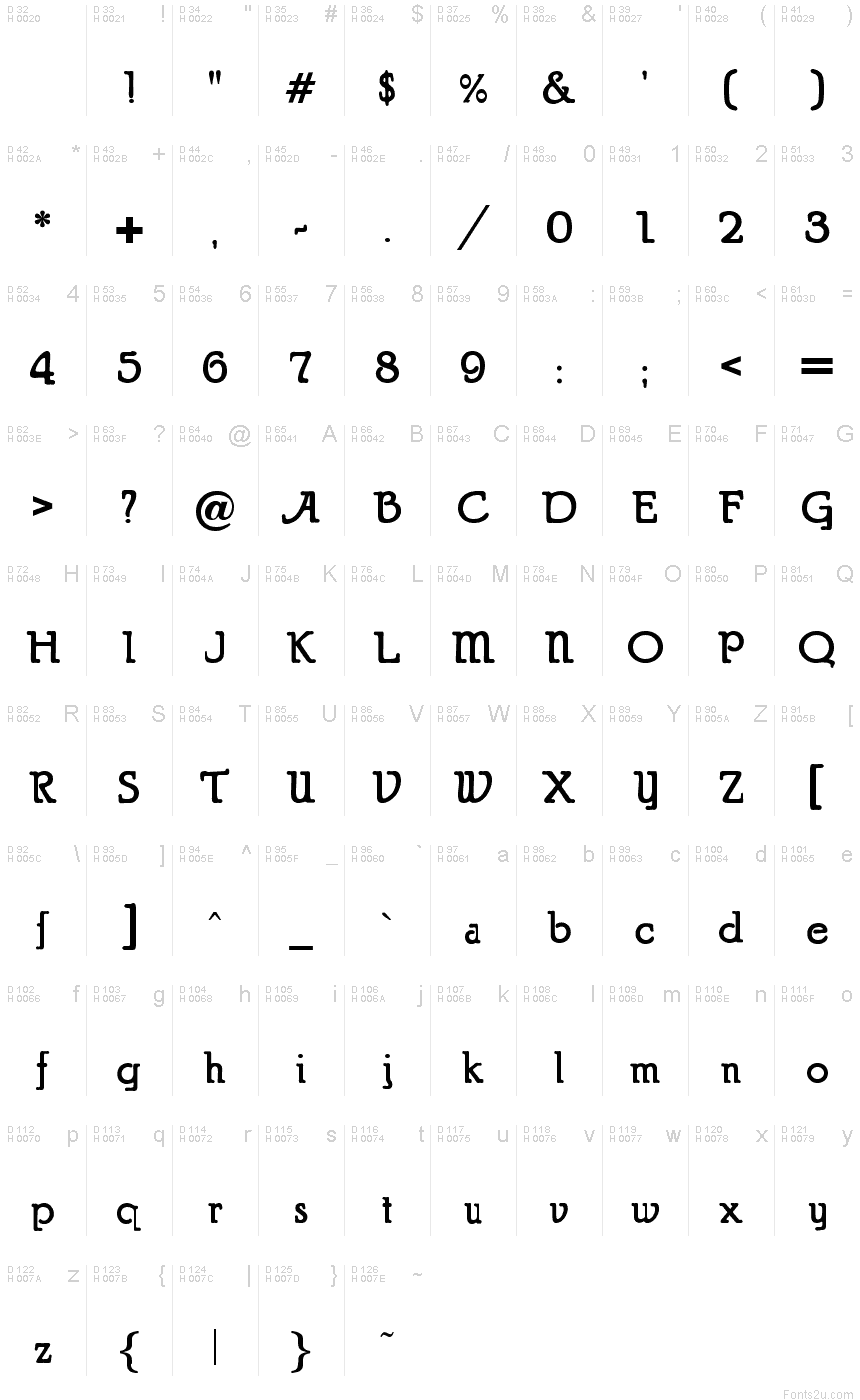
Puritan Alternate Bold
Puritan Alternate Bold di Typographer Mediengestaltung è un carattere display serif gratuito dallo stile retrò, che evoca il calore degli inizi del XX secolo. Le lettere appaiono larghe e quasi scritte a inchiostro, con grazie arrotondate, giunzioni morbide e un ritmo leggermente irregolare che impedisce al peso del carattere di risultare rigido o troppo formale.
È l'ideale per titoli di locandine, copertine di libri, branding di locali, packaging vintage e testate di riviste dove si cerca un'atmosfera d'epoca senza eccessi decorativi. Essendo un font gratuito, funziona bene anche per brevi titoli o iniziali di grandi dimensioni, perché le curve corpose e i dettagli vivaci conferiscono carattere e pienezza visiva anche a poche lettere.